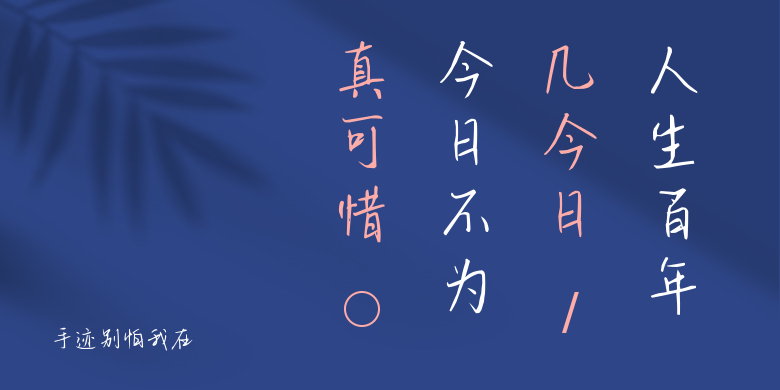
手迹别怕我在
手迹别怕我在,这款字体结构工整、笔画清晰,兼顾美观与易读性,适用于标题、正文、海报、包装、LOGO 等多种场景。字形优雅稳定,风格百搭耐看,适配日常排版与创意设计,让文字呈现更舒适、更具质感。手迹别怕我在一笔一画,皆是细节,以均衡的比例、流畅的线条打造舒适视觉体验,字形端正大气,风格简约现代。无论是商业设计、品牌宣传还是日常排版,都能轻松驾驭,让文字更有格调与力量。手迹别怕我在字体下载。